Jak korzystać z czcionek Google z WordPress?
Współczesna sieć to przede wszystkim doświadczenie użytkownika. Firmy inwestują dużo czasu i pieniędzy, aby zapewnić odwiedzającym ich witrynę jak najlepsze wrażenia podczas przeglądania ich witryny.
Reprezentacja tekstowa odgrywa integralną rolę w estetyce serwisu. Nie ma znaczenia, jak dobra jest jakość Twoich treści; jeśli czytanie nie jest przyjemne i jest zbyt zagracone dla czytelników, wszystkie twoje wysiłki idą na marne.
Chociaż dostępnych jest wiele opcji typograficznych, najłatwiejszym sposobem uzyskania dostępu do setek profesjonalnych czcionek (bezpłatnie) jest użycie czcionek Google w witrynie WordPress.
W tym poście przedstawię Ci instrukcje krok po kroku, aby dowiedzieć się, jak ręcznie dodać czcionki Google WordPress do swojej witryny i za pomocą wtyczki Easy Google Fonts . Pokażę Ci również najlepsze czcionki, których możesz użyć, aby poprawić czytelność treści Twojej witryny.
1- Czym są czcionki Google WordPress i dlaczego warto ich używać?
Zanim zaczniemy, przyjrzyjmy się szybko, czym są czcionki Google wraz z kluczowymi zaletami ich używania w witrynie WordPress.
Google Fonts to biblioteka darmowych licencjonowanych czcionek wprowadzona w 2010 roku. Możesz korzystać z niesamowitej biblioteki Google Fonts, wywołując dostarczony interfejs API. Ciekawostką jest to, że możesz używać 877 czcionek zoptymalizowanych pod kątem sieci – za darmo. To jest niesamowite. Zawiera interaktywny katalog stron internetowych, który umożliwia wyszukiwanie określonych typów czcionek i testowanie ich w przeglądarce internetowej.
Korzystanie z WordPress Czcionki Google ma wiele zalet. Można ich używać za darmo (nawet w przypadku projektów komercyjnych), wstępnie hostowane (więc nie zajmują zasobów serwera) i można je pobrać (można ich używać w wersji drukowanej).
Istnieje wiele stron internetowych, które obecnie wykorzystują czcionki Google w WordPress na swoją korzyść. Wszystkie nowoczesne motywy obsługują korzystanie z czcionek Google.
Jeśli jesteś gotowy, aby odświeżyć typografię swojej witryny za pomocą łatwych w użyciu czcionek internetowych, wszystko, co musisz zrobić, to znaleźć odpowiednie czcionki i używać ich w witrynie WordPress.
2- Jak ręcznie dodać czcionki Google do WordPress?
Google Fonts eliminuje większość problemów związanych z osadzaniem rodzin czcionek w Twojej witrynie. Jest to biblioteka online, którą można wywołać w dowolnym projekcie internetowym, jak każdy inny skrypt JS lub CSS.
W tej sekcji zademonstruję, jak ręcznie zainstalować czcionki Google w witrynie WordPress.
Krok 1: Znajdź czcionkę, którą chcesz dodać do swojej witryny
Aby rozpocząć, przejrzyj katalog czcionek Google i wybierz czcionkę, której chcesz użyć w swojej witrynie WordPress. Jeśli masz już określony krój pisma, możesz go po prostu wyszukać za pomocą pola wyszukiwania na prawym pasku bocznym.
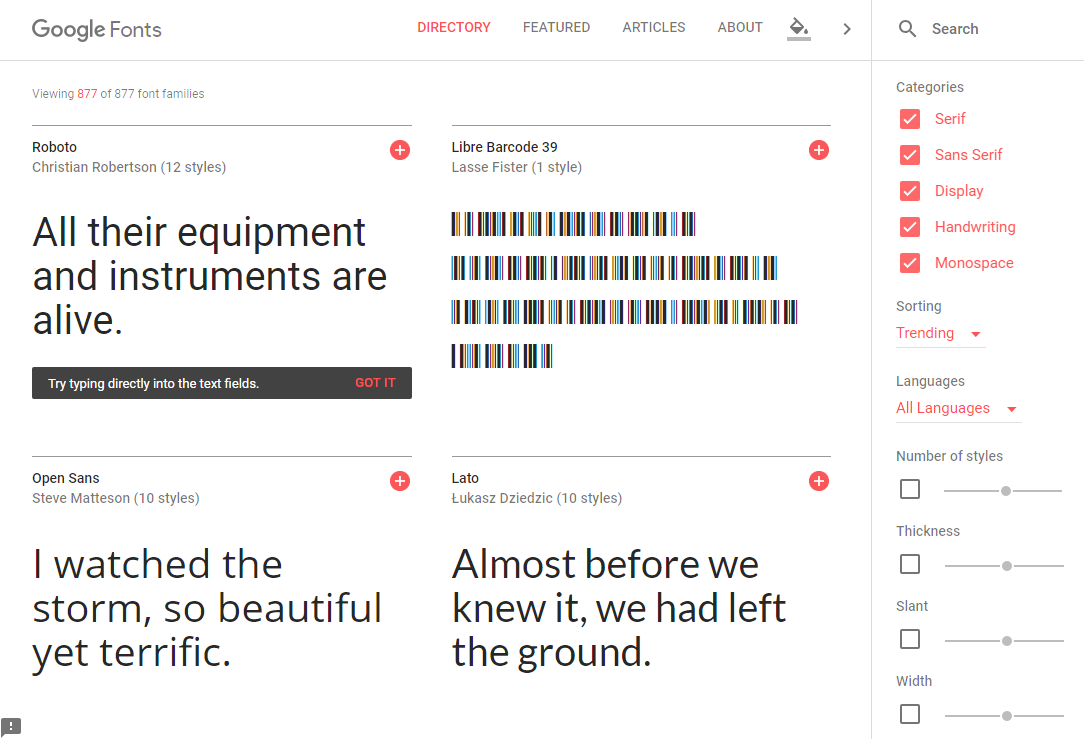
Możesz także filtrować czcionki według kategorii, języków, liczby stylów, grubości, pochylenia i szerokości lub sortować je według daty dodania, alfabetycznie, trendów lub popularności.
- Są to czcionki z małymi liniami na końcu kresek literowych, np. Times New Roman i Courier .
- Bezszeryfowy. Czcionki, które nie mają małych linii na końcu pociągnięć liter, to czcionki bezszeryfowe, np. Helvetica i Roboto .
- Czcionki ekranowe są używane głównie do dużych tekstów, np. tytułów.
- Czcionki, które mają wygląd odręczny, np. Pacifico .
- Czcionki, które mają dokładnie takie same odstępy między wszystkimi znakami, np. Source Code Pro .
Jedną z największych zalet korzystania z funkcji interaktywnego katalogu Google Fonts jest to, że możesz szybko wyświetlić podgląd czcionek, które Cię interesują. Wszystko, co musisz zrobić, to kliknąć pole z czcionką i wpisać w nim tekst.
Na potrzeby tego samouczka skorzystam z Open Sans .
Krok 2: Dodaj czcionki do swojego wyboru
Teraz, gdy wiemy, z jaką czcionką będziemy korzystać, dodajmy ją do naszego wyboru. Możesz to zrobić, klikając znak plus (+) w prawym górnym rogu pola rodziny czcionek.
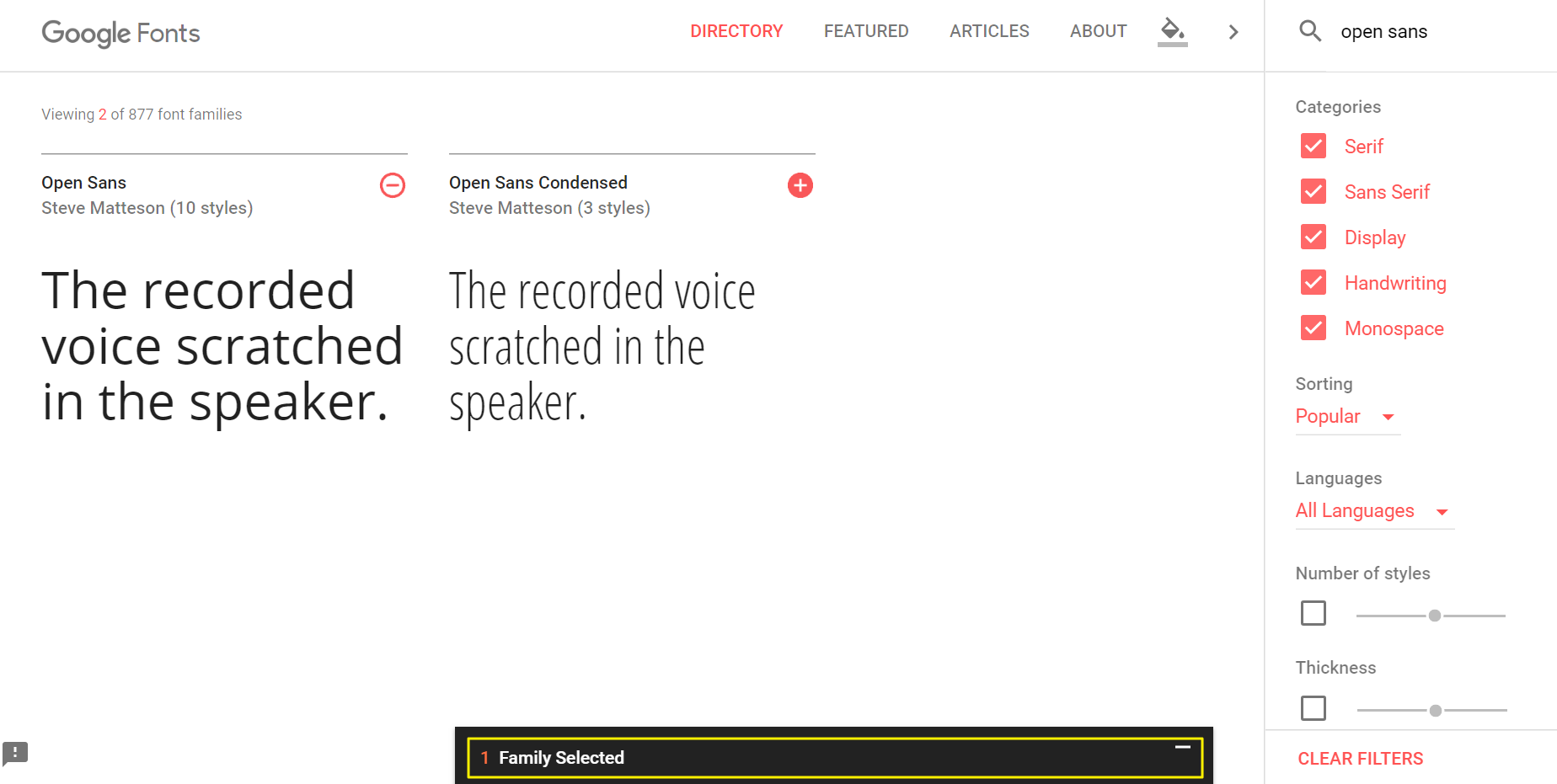
Do wyboru możesz dodać dowolną liczbę rodzin czcionek. Gdy wszystko będzie gotowe, kliknij czarny pasek Wybrana rodzina X u dołu ekranu, aby wyświetlić swój wybór.
Krok 3: Dostosuj czcionkę
Pasek Wybrana rodzina X otwiera okno z dwiema zakładkami – Osadź i Dostosuj . Zanim osadzimy rodzinę czcionek w naszej witrynie WordPress, poświęcimy chwilę, aby ją nieco dostosować.
Na ekranie Dostosuj zaznacz pola dla stylów i języków, których chcesz używać w swojej witrynie.
Pamiętaj, że im więcej stylów czcionek i języków wybierzesz, tym dłużej zajmie wczytanie stron Twojej witryny. Na tym samym ekranie zobaczysz wskaźnik czasu wczytywania, który informuje, czy Twój wybór spowolni czas wczytywania.
P. Jakie czcionki są dostępne w WordPressie?
WordPress obsługuje wszystkie czcionki, które można zaimportować za pomocą wtyczek lub skonfigurować ręcznie w folderze czcionek. Domyślnie WordPress ma domyślną czcionkę, którą możesz zastąpić inną niestandardową czcionką.
P. Jaka jest najlepsza czcionka dla stron internetowych?
Nie ma jednej „najlepszej” czcionki dla strony internetowej. Chociaż istnieją sprawdzone metody wybierania czcionek do witryn internetowych, zawsze warto przetestować kilka rodzin czcionek, aby znaleźć najlepsze dopasowanie do typografii witryny.